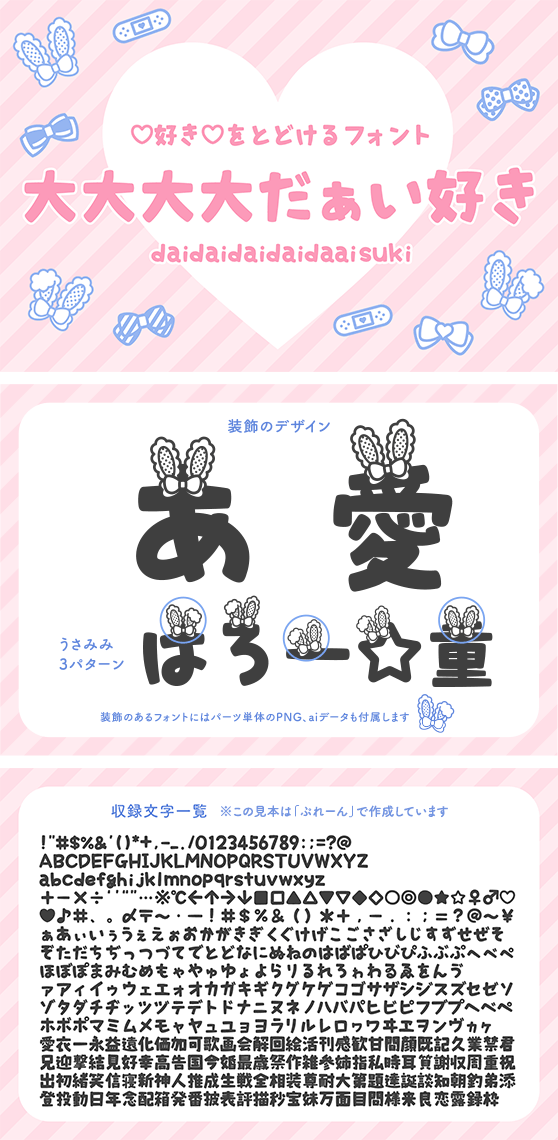
大大大大だぁい好き うさみみ
daidaidaidaidaaisuki_bunny
コンセプトは「好きを届けるフォント」
「大大大大だぁい好き」は、推しを応援したい、または自分を推してほしい、そんな場面で使いたくなるフォントファミリー。
ひらがな、カタカナ、英数、一部の記号と、一部の漢字(配信者の方や推し活に使いやすいものを厳選した115字)を収録した日本語OpenTypeフォントです。
装飾のない「ぷれーん」の他、リボン、絆創膏、うさ耳(本製品)の装飾がついたバージョン、それらをフル収録したお得な4書体セットがあります。
本製品「うさみみ」も縦書きは可能ですが、耳が重なってしまうため文字間調整が必須となります。
ひらがな、カタカナ、英数、一部の記号、一部の漢字(推し活やサムネイルの見出しに使いやすい文字を厳選した115字)